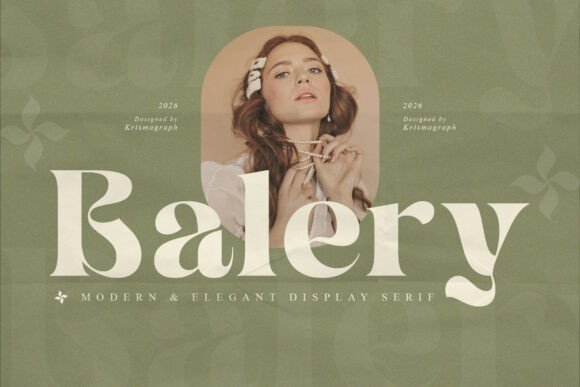
Balery
Die richtigen Designelemente zu finden, kann eine Herausforderung sein, aber Balery bietet eine außergewöhnliche Sammlung, die Ihre Arbeit sofort aufwertet.
Egal, ob Sie POD-Produkte (Print on Demand), Hochzeitseinladungen oder Social-Media-Grafiken erstellen, Balery ist die ideale Wahl.